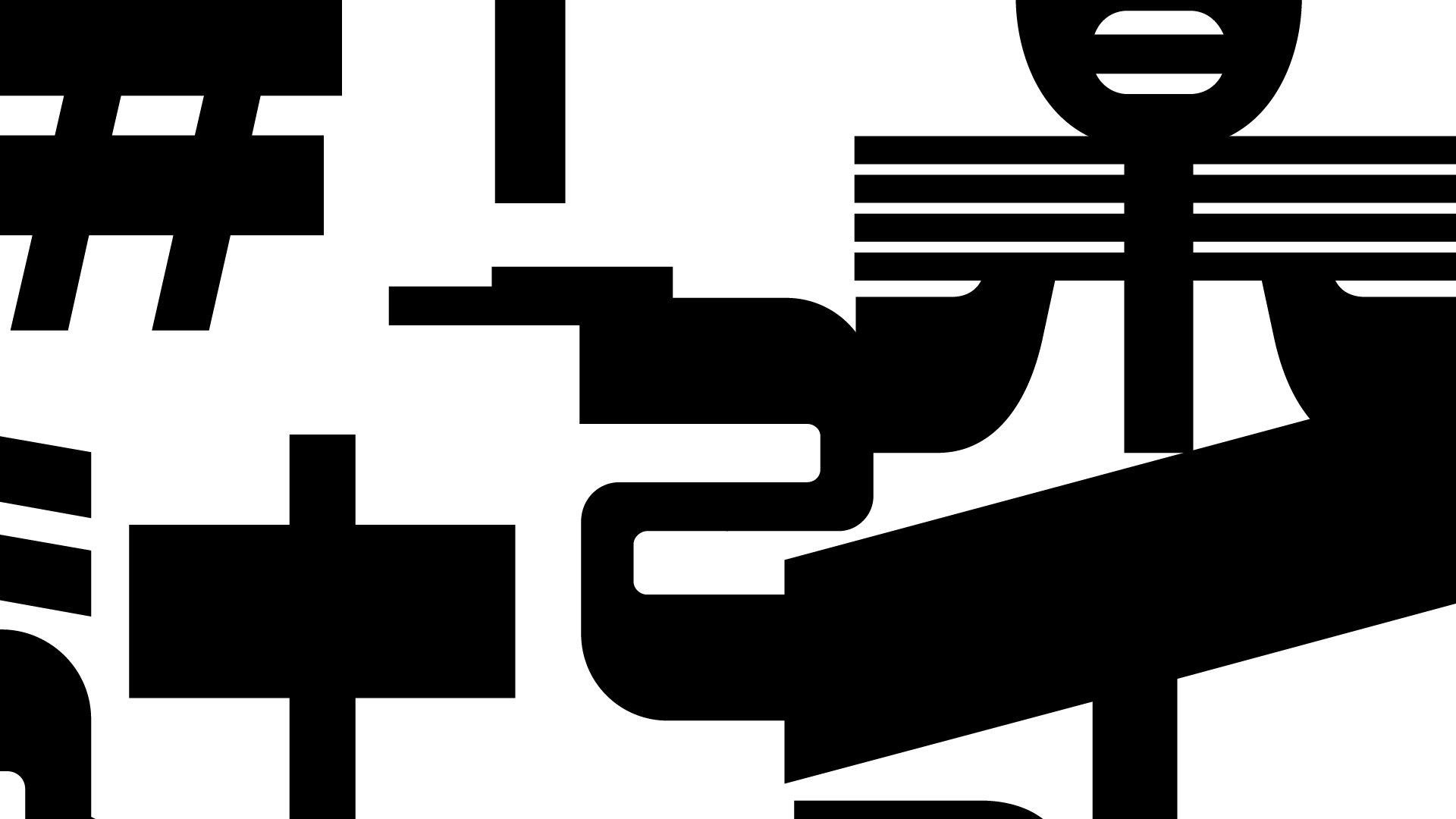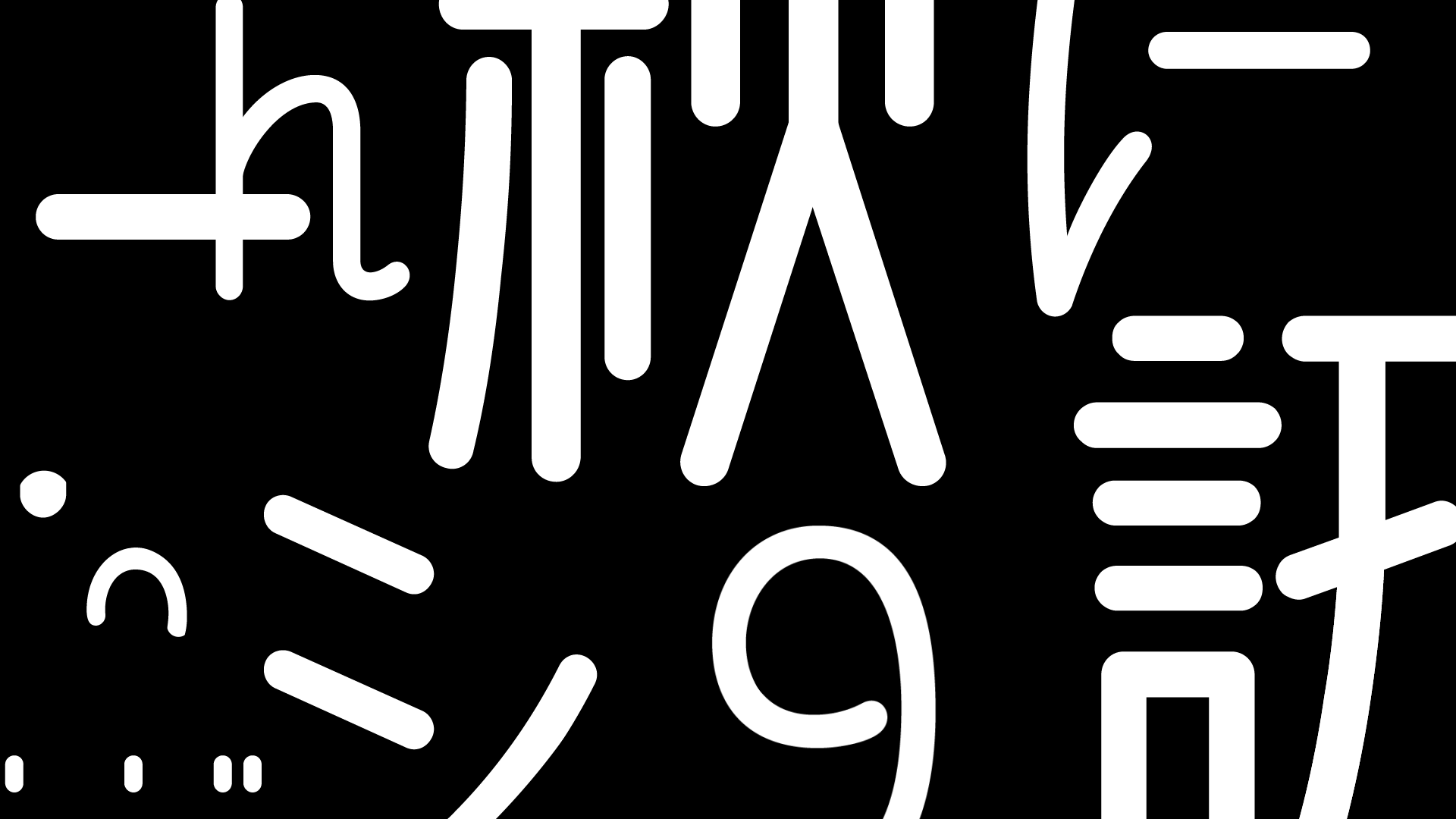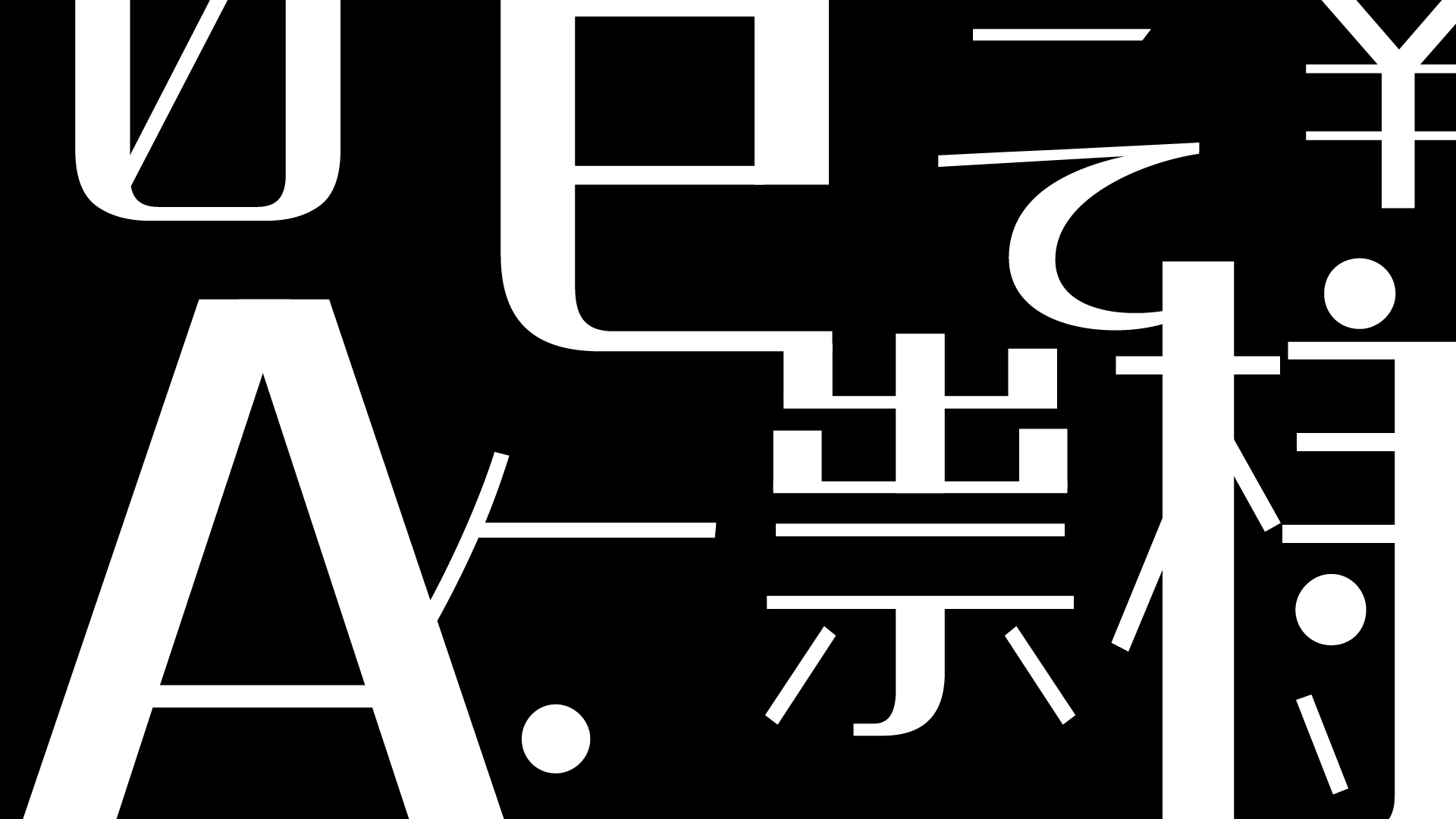
コミュニケーションアーツ入賞
この度、コミュニケーションアーツ主催2021 Advertising部門に入賞し、
同社出版のCommunication Arts11/12月号【Advertising Annual】に楽フォントの作品が掲載されました。
作品「楽」について
楽フォントでは、中国古来の漢字文化を日本語フォントに取り入れ、これまでにない多彩なフォントの制作に挑戦しています。作品「楽」は、楽フォント書体の楽しさ・優美さを体感的に視ていただけるプロモーションビデオになっています。
多種多様なフォントを通じて人と人が繋がっていき、書体や文字に対して難しく捉えすぎず、楽しく豊かな心をもつ人々がこれからも増えていく未来を願い制作された作品です。
※※使用されている書体※※
玲優体・親剛体・書房体・書房体H・明朗体・文尚体・喜縁体